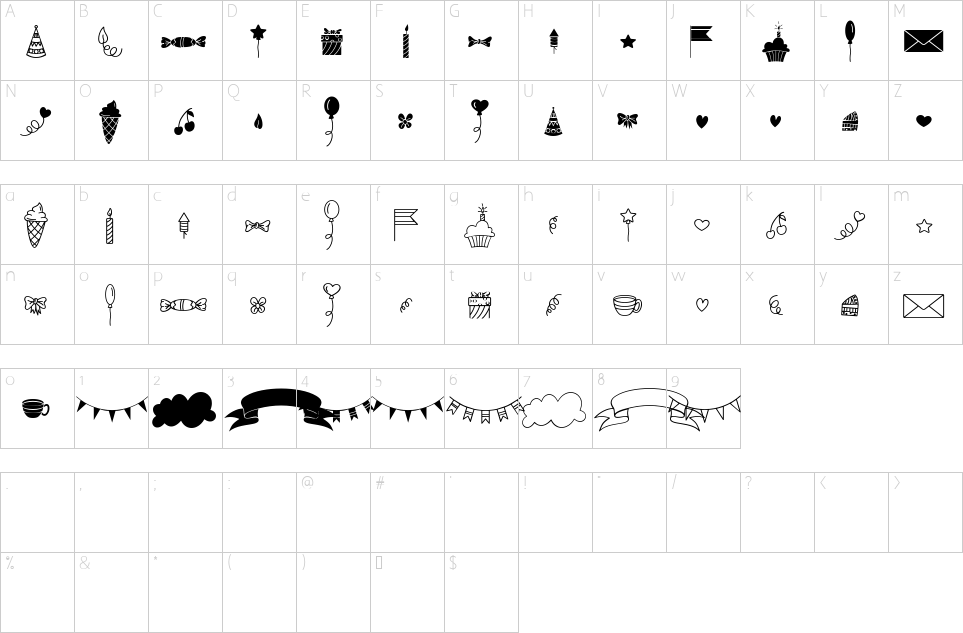
A fonte Habede Extra Doodles oferece um toque divertido e descontraído para qualquer projeto de design gráfico. Desenvolvida pelo designer Situjuh Nazara, essa fonte foi projetada para dar um charme único a qualquer texto ou design. Com seu design de doodle, Habede Extra Doodles é uma escolha perfeita para quem procura algo diferente e criativo para ilustrar mensagens em sua próxima produção. Foi baixada mais de 16.721 vezes, demonstrando seu valor e alegria na comunidade de designers. Seja você um amante de doodles, um designer de identidade ou simplesmente aquele que busca algo divertido para adicionar um toque personalizado aos seus projetos, Habede Extra Doodles é uma fonte que merece uma chance.